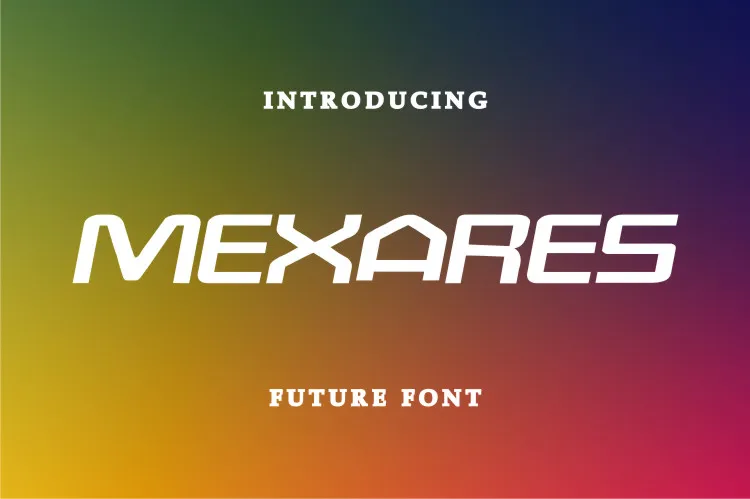
A fonte “Mexares Font” é uma opção moderna para designers que buscam adicionar elegância e originalidade a seus trabalhos digitais. Desenvolvida pela letterfiastudio, ela se destaca como um estilo clean para aplicações gráficas em sites, logomarcas ou qualquer outro tipo de trabalho digital que desejam um toque inteligente e cool. Suas linhas limpas e precisas tornam-a uma escolha ideal para criar designs inovadores e modernos. Não importa o projeto específico, “Mexares Font” é versátil e pode ser aplicada com sucesso em vários contextos para destacar seus trabalhos de design.